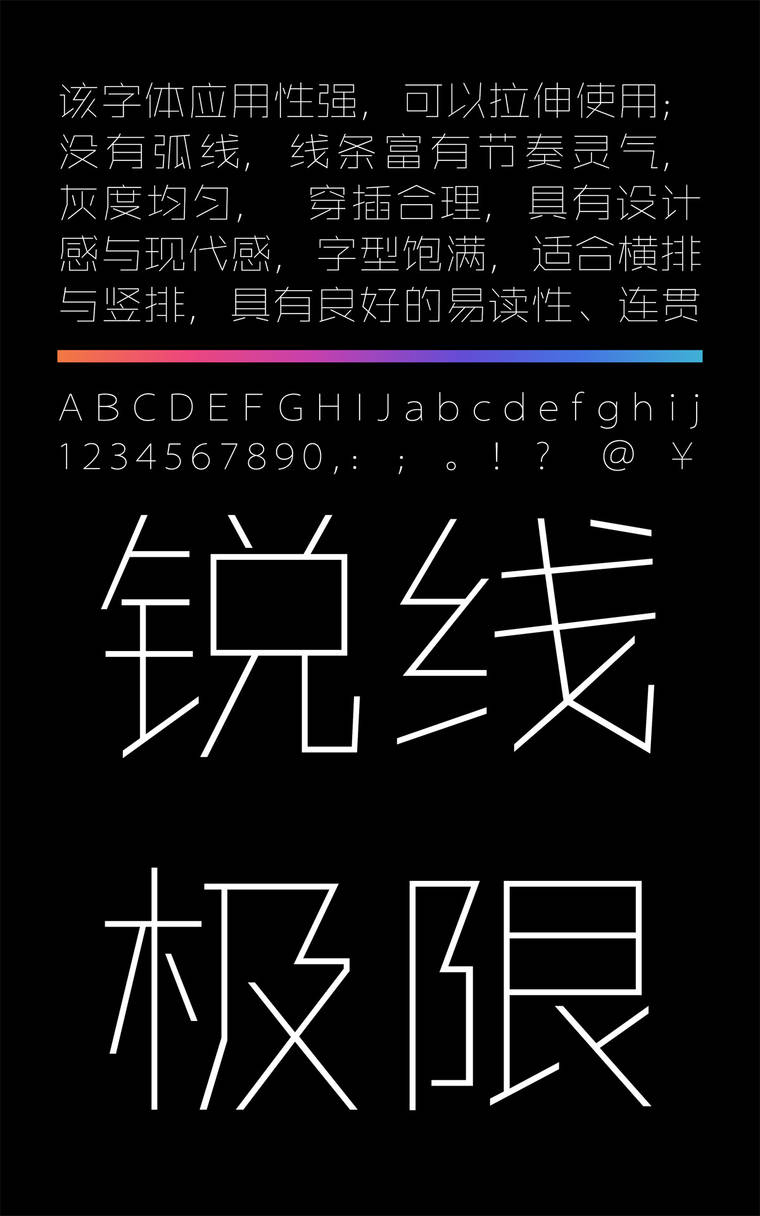
锐字锐线极限黑简1.0
锐字锐线极限黑简1.0,这款字体结构工整、笔画清晰,兼顾美观与易读性,适用于标题、正文、海报、包装、LOGO 等多种场景。字形优雅稳定,风格百搭耐看,适配日常排版与创意设计,让文字呈现更舒适、更具质感。锐字锐线极限黑简1.0一笔一画,皆是细节,以均衡的比例、流畅的线条打造舒适视觉体验,字形端正大气,风格简约现代。无论是商业设计、品牌宣传还是日常排版,都能轻松驾驭,让文字更有格调与力量。锐字锐线极限黑简1.0字体下载。
字体特征:该字体应用性强,可以拉伸使用;没有弧线,线条富有节奏灵气, 灰度均匀, 穿插合理,具有设计感与现代感,字型饱满,适合横排与竖排,具有良好的易读性、连贯的阅读性。